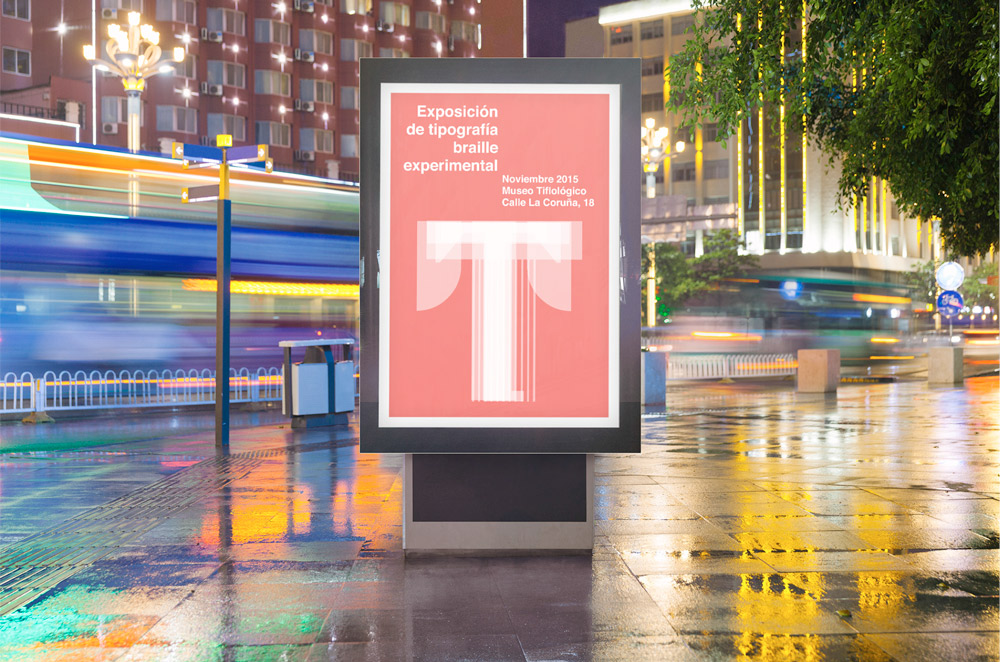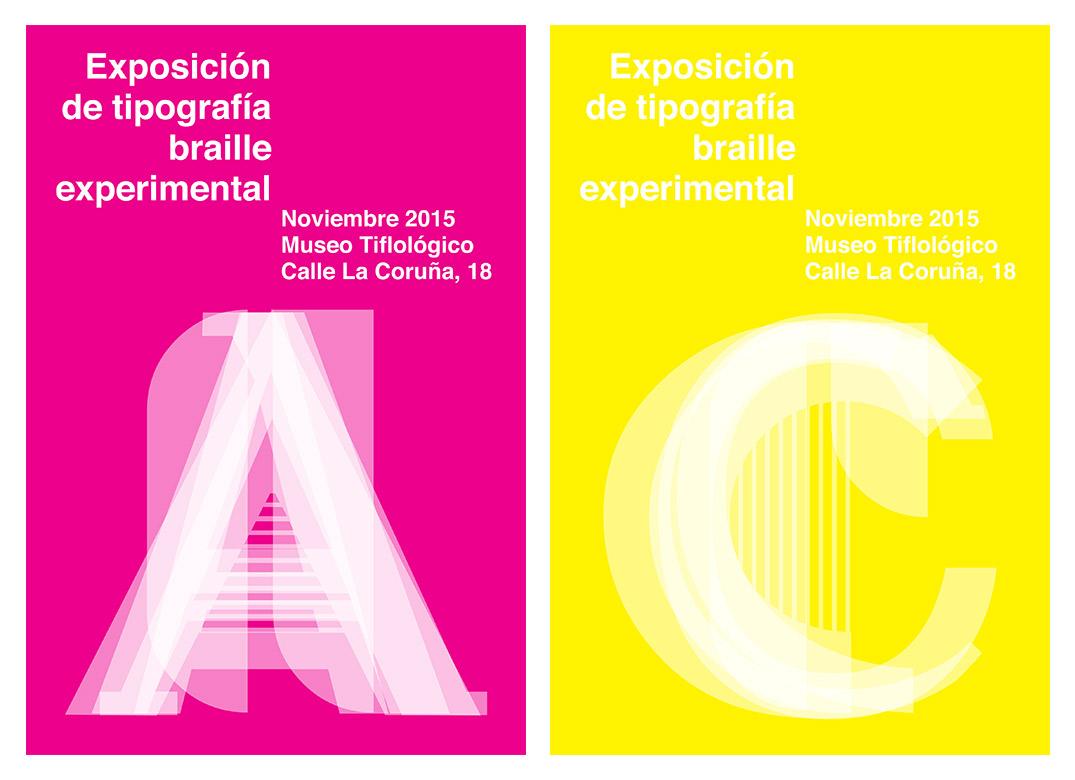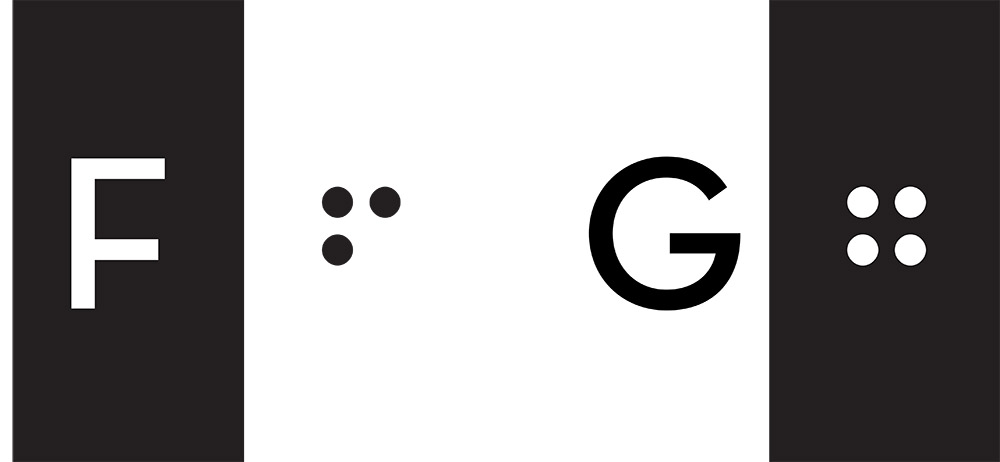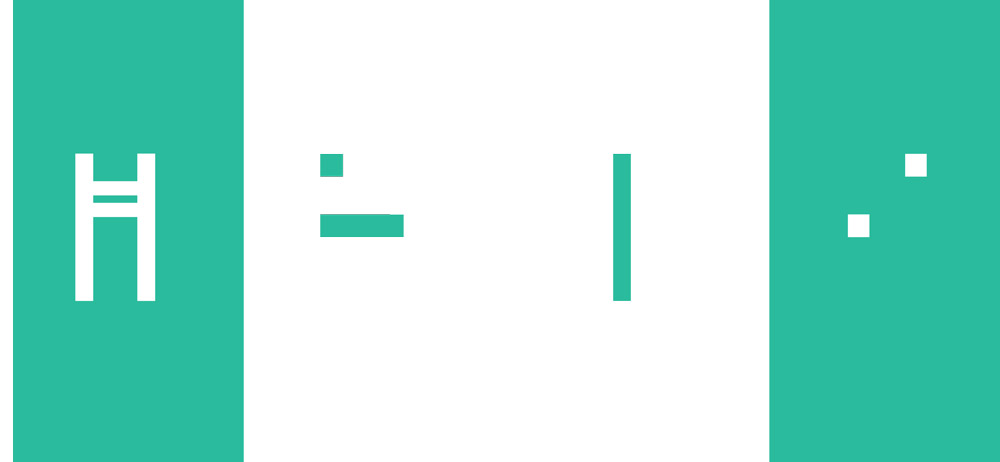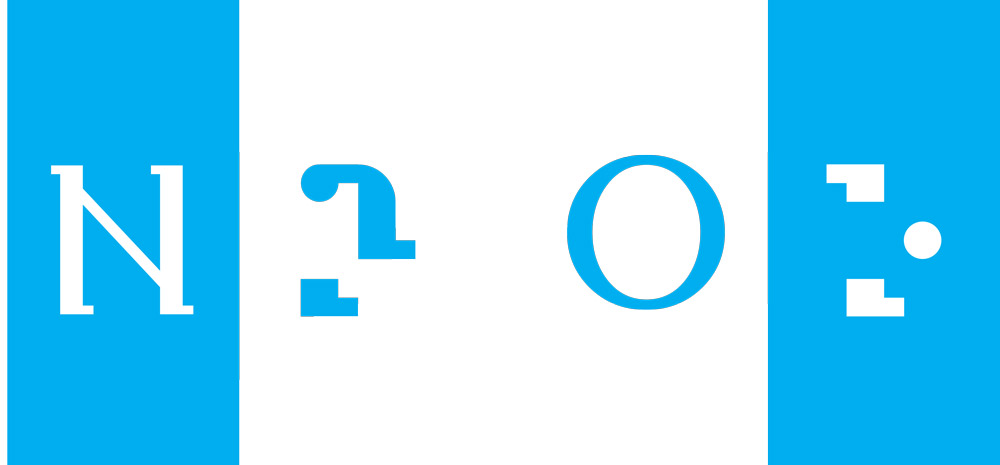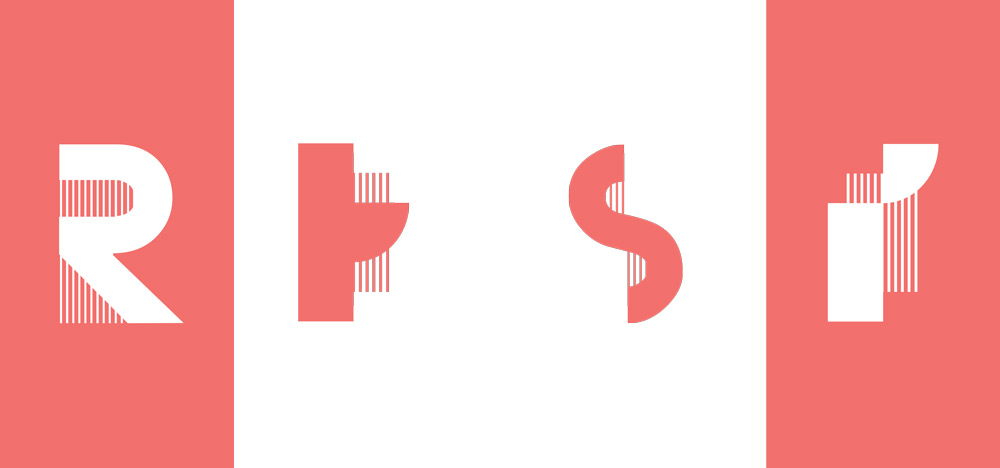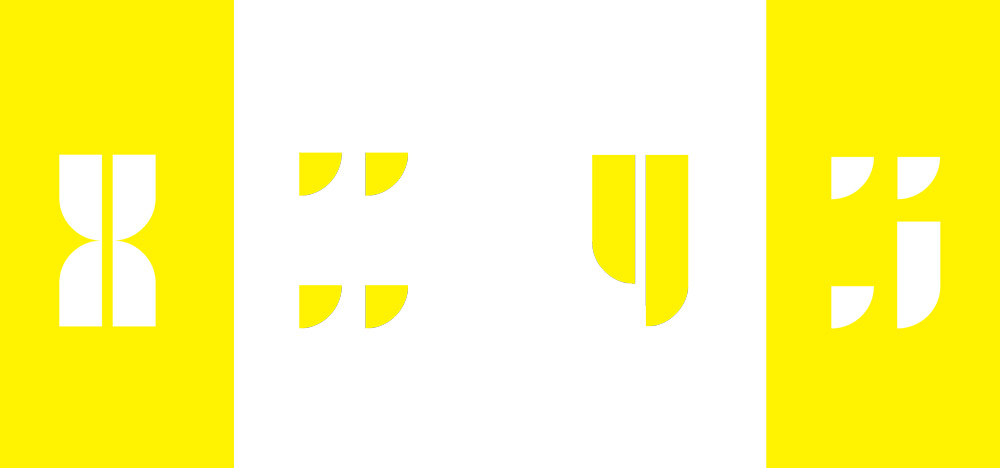
Tactografia vs Tipografia
Entre els projectes de final de grau d’ESNE (escola universitària de disseny, innovació i tecnologia) hem descobert aquesta joia creativa.
Tactography, a walk on the blind side de Jacobo Olmedo Iglesias.
Un exercici tipogràfic d’una brillantor i originalitat excepcionals, on el seu creador, Jacobo Olmedo, ha aconseguit desenvolupar una sèrie de tipografies totalment noves pensades per al Braille.
A partir de fonts creades als segles XIX i XX, que han estat referents en el món del disseny fins avui, ha creat tot un ventall de tipografies Braille.
Jacobo va iniciar el seu estudi centrant-se en Charles Rennie Mackintosh, arquitecte, dissenyador gràfic i vinculat a l’Art Deco, el Cubisme i el Futurisme.
També va posar el focus en Peter Behrens, arquitecte, dissenyador i creatiu multidisciplinari, membre de la Deutcher Werkbund (ara Bauhaus) i pintor abstracte.
En Josef Albers, també dissenyador, poeta, tipògraf, membre de la Bauhaus i pintor abstracte.
I finalment en Max Miedinger, tipògraf suís eternament recordat per la creació de l’Helvetica el 1957.
Amb tota la passió que es pot esperar, Jacobo aconsegueix, a partir del seu profund estudi d’aquestes eminències de la tipografia, desenvolupar una sèrie de noves tipografies per a persones amb discapacitat visual.
El seu principal objectiu és millorar el llenguatge dels invidents, optimitzar els caràcters i afavorir una major inclusió social a través del llenguatge.
Amb això, busca unir el món de la lectura, inicialment visual, amb el món tàctil. La vista i el tacte es fusionen per crear una nova experiència sensorial, encara sense nom.
Trenca i dissol la barrera entre sentits que tan arrelada està a la nostra societat. La idea és potent i innovadora, i creiem que mereix una menció destacada, tant pel seu significat com pel valor del resultat final.
Ens encantaria tenir l’oportunitat de treballar amb aquestes tipografies en algun projecte de disseny gràfic i, de fet, estem convençuts que a Barcelona no trigarà gaire a sorgir algun client interessat en una proposta d’aquestes característiques.